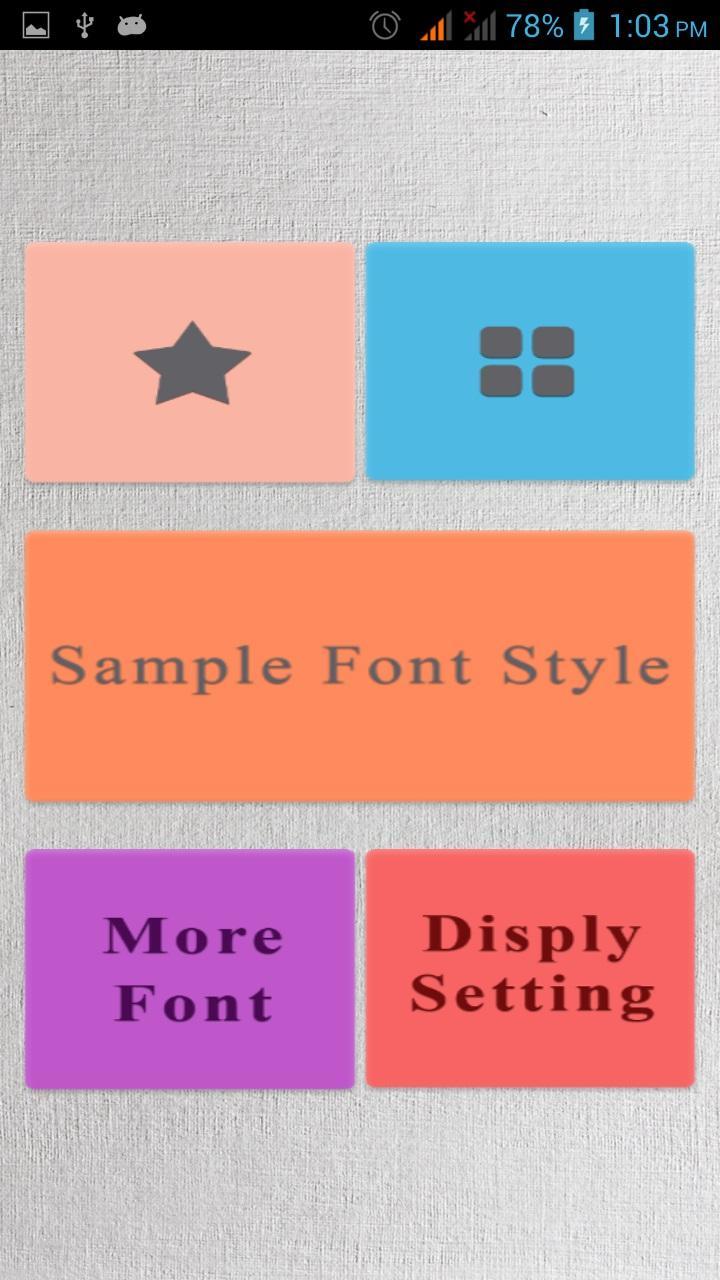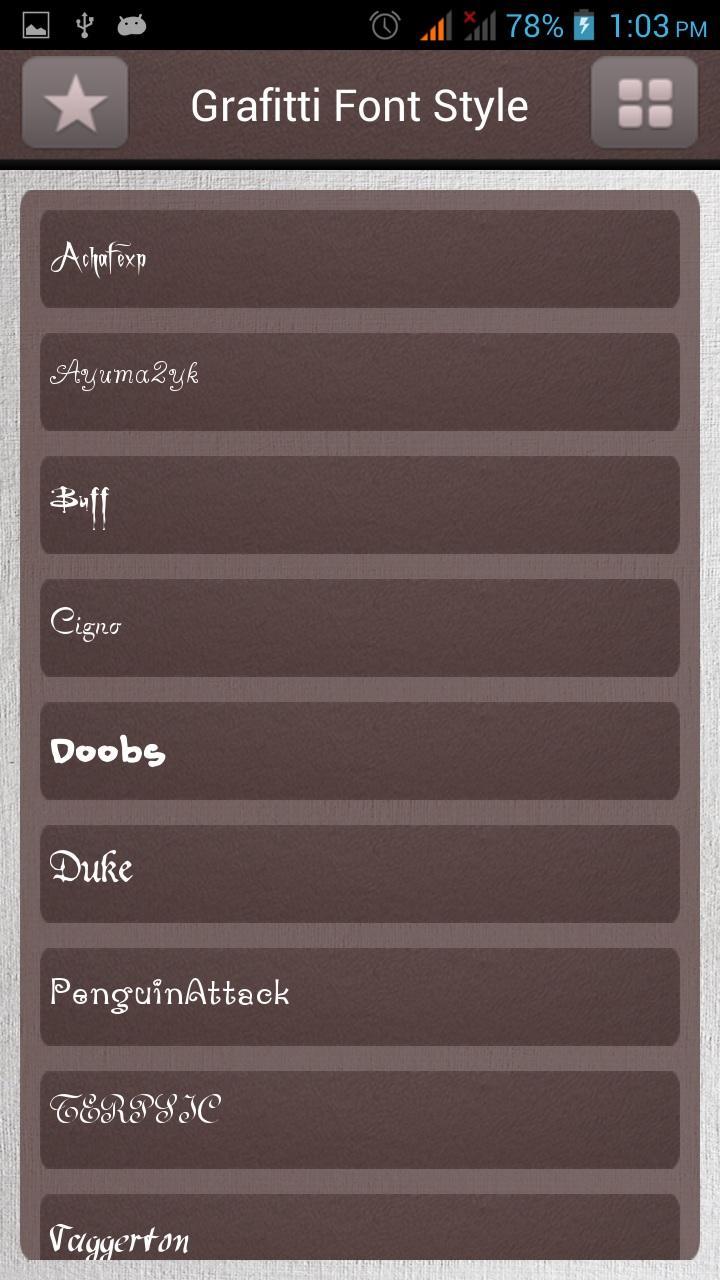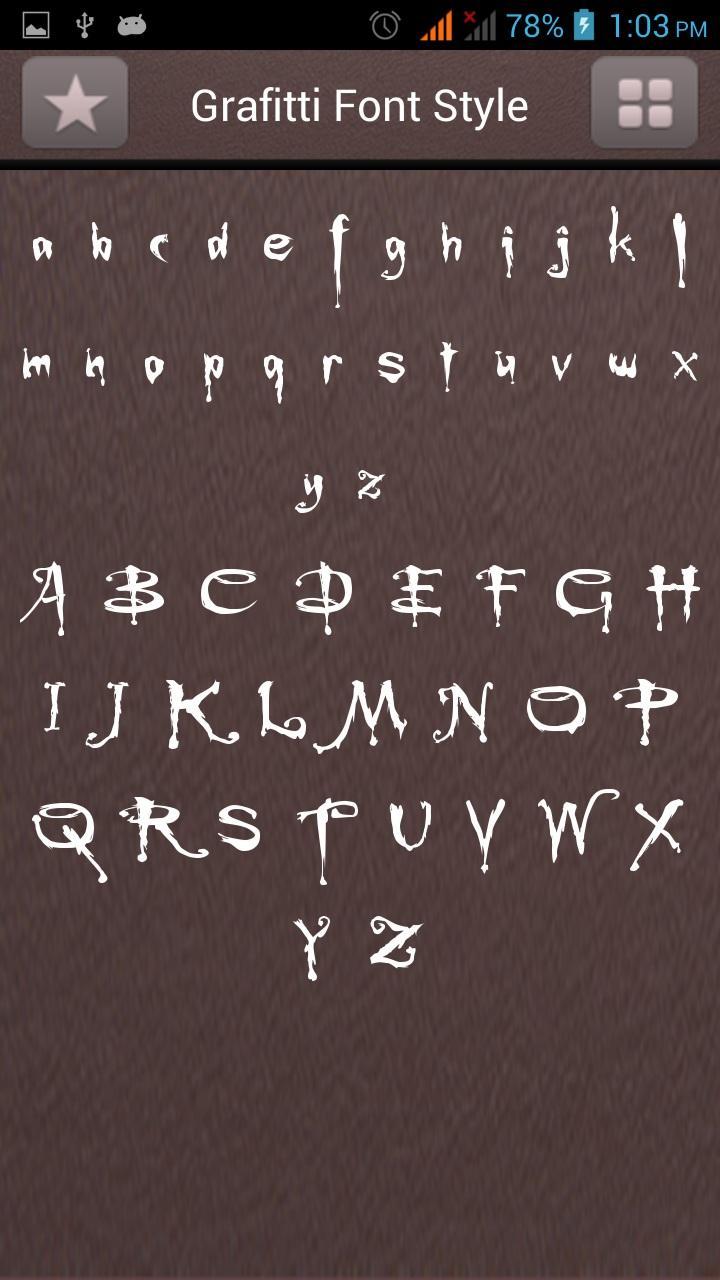
Graffiti Font Style
A fonte de graffiti é usada para alterar a mudança do estilo da fonte do dispositivo.
Fonte de graffiti FOT Usada para definir suavemente apontados com o estilo graffiti e aplicar no seu dispositivo de telefone.